Katharina Pieper
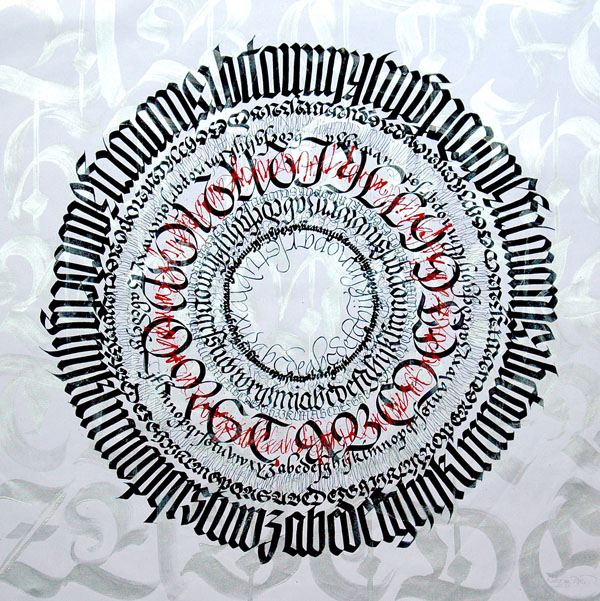
Fraktur - Textur - Bastarda - Kreis,
in der Ausstellung "Silver Calligraphy" mit Achyut Palav, Nehru Center Art Gallery, Mumbai 2011